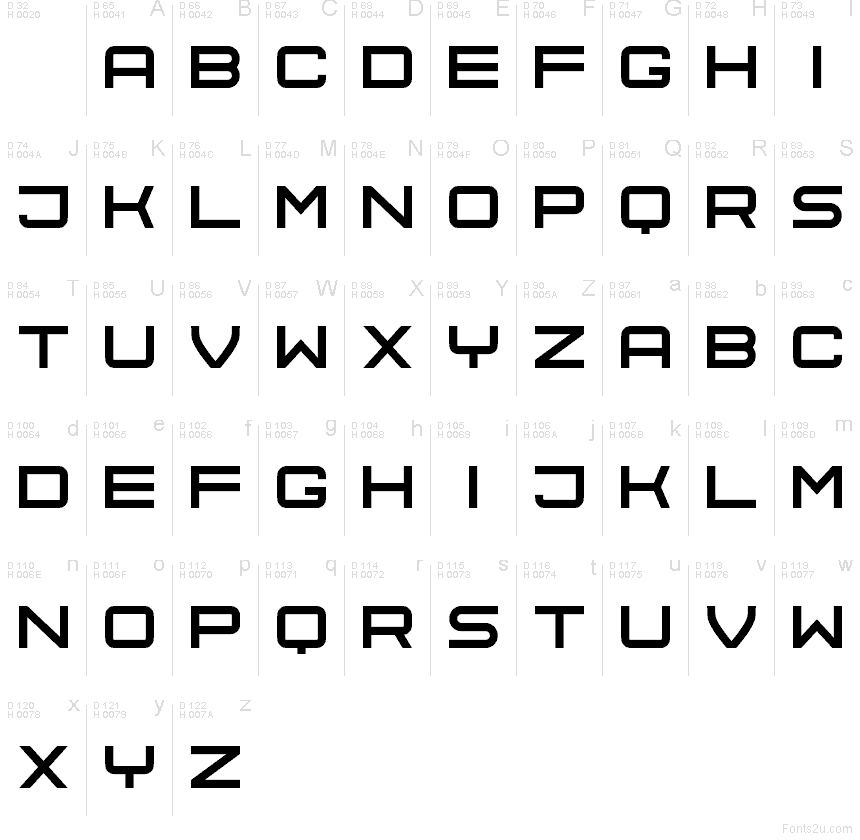
New Brush Book, ktorého autorom je Vladimir Nikolic, je bezplatné geometrické techno písmo zložené z veľkých písmen, postavené na širokých ťahoch, ostrých diagonálach a hladko zaoblených prechodoch. Jeho futuristický charakter vychádza z napätia medzi otvorenými, hranatými tvarmi písmen a ťažšími zaoblenými prvkami, čo vytvára kompaktný rytmus s výrazne digitálnym nádychom.
Tento bezplatný font je vhodný na sci-fi plagáty, obaly elektronickej hudby, herný branding, eventovú grafiku, obalový dizajn či filmové titulky. Odvážna geometria najlepšie vynikne v krátkych nadpisoch a titulných nápisoch, kde majú ostré uhly a zametajúce krivky dostatok priestoru na to, aby definovali vizuálnu náladu.